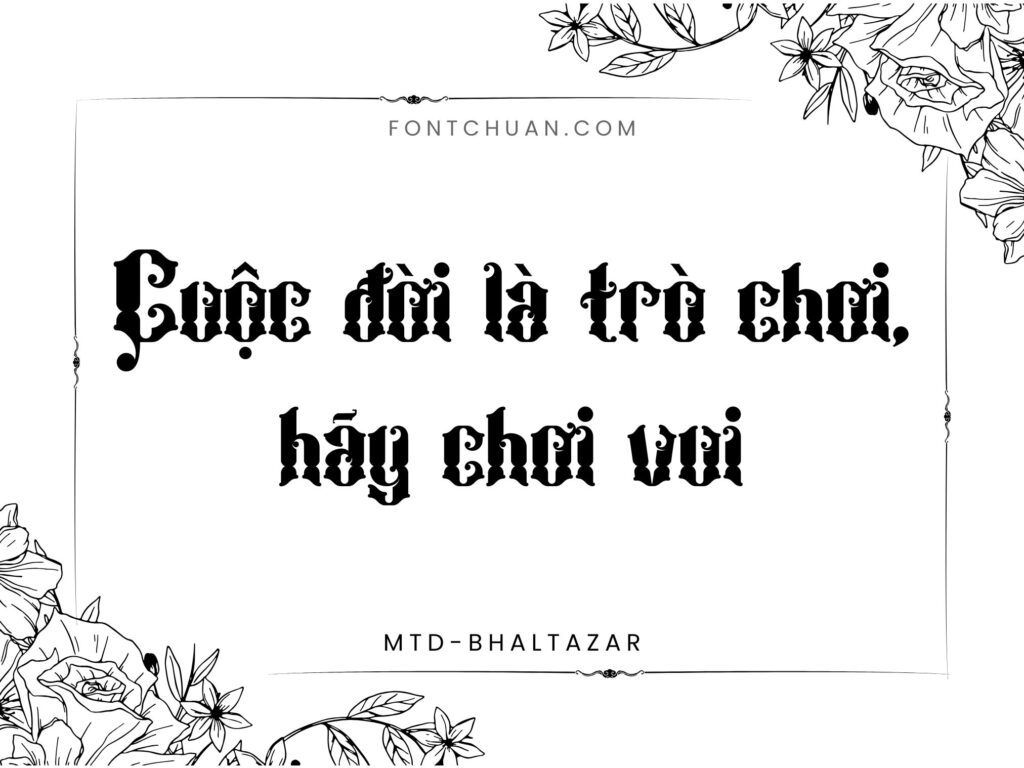
Font MTD Bhaltazar Việt Hóa
Bhaltazar là một font chữ mạnh mẽ mang phong cách hiện đại kết hợp với đường nét cổ điển. Với các ký tự chắc chắn, có độ dày vừa phải và các đường nét tinh tế, font này mang lại cảm giác chuyên nghiệp và sang trọng. Để giúp cộng đồng thiết kế Việt Nam tiếp cận dễ dàng hơn, Mộc Hạ đã Việt hóa font Bhaltazar, giúp nó hỗ trợ đầy đủ tiếng Việt cùng hơn 200 ngôn ngữ khác. Phiên bản Bhaltazar Việt hóa đã được thành viên Font Chuẩn sưu tầm và đăng tải nhằm phục vụ cộng đồng thiết kế, mang đến sự lựa chọn đa dạng hơn cho các dự án sáng tạo.
Về đặc điểm thiết kế, Bhaltazar sở hữu những đường nét cân đối với độ tương phản cao, giúp tạo nên sự nổi bật trong các thiết kế tiêu đề, logo và thương hiệu. Font này có tính ứng dụng cao, đặc biệt phù hợp với các thiết kế liên quan đến quảng cáo, công nghệ, bất động sản và giáo dục. Ngoài ra, Bhaltazar cũng rất thích hợp cho các sự kiện như Valentine, Sinh nhật và các lễ hội, nơi cần một phong cách chữ rõ ràng và ấn tượng.